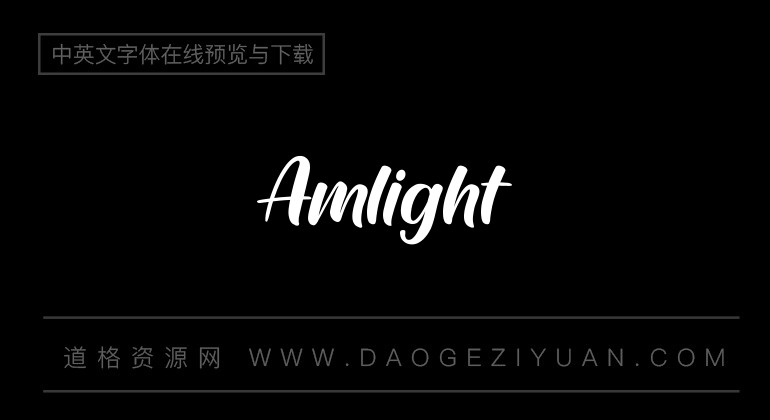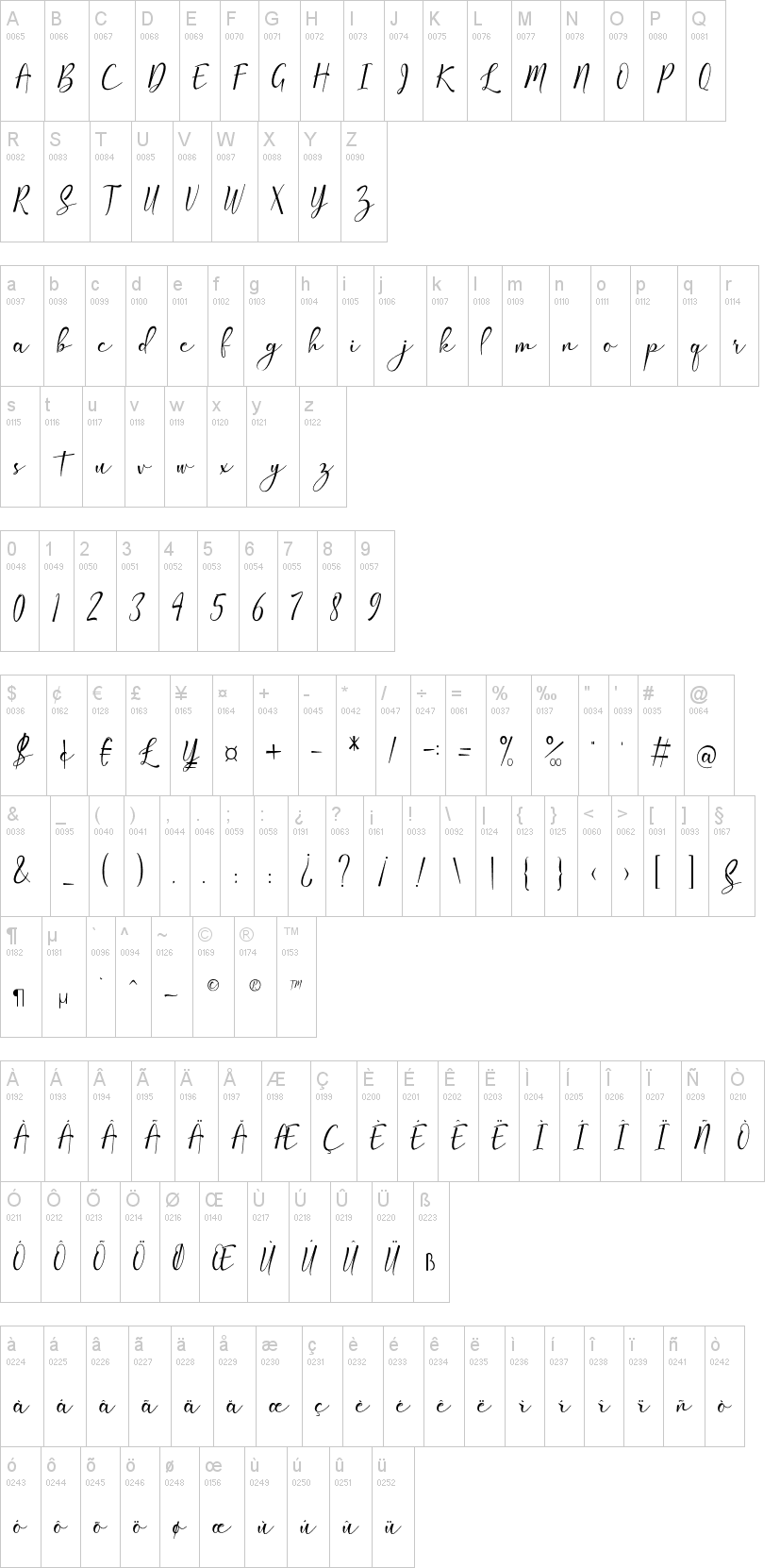
Amlight
Amlight 是一款简洁而优雅的英文字体,它由 Fontfabric 公司设计,拥有简洁的线条和友好的风格,具有清晰的外观和柔和的触感。Amlight 字体有三种不同的重量:Light,Regular 和 Bold,每种重量都有大小写字母、数字和标点符号,可以满足您的多种设计需求。Amlight 字体可以用于各种平面设计,如海报、广告、商标、书籍封面等,也可以用于网页设计和应用程序界面设计。
Amlight是一款非常不错的手写艺术字体,具有很好的视觉感,适合于文化类的宣传设计、商业类品牌的广告和产品包装设计以及个性化文字排版等较多场景。